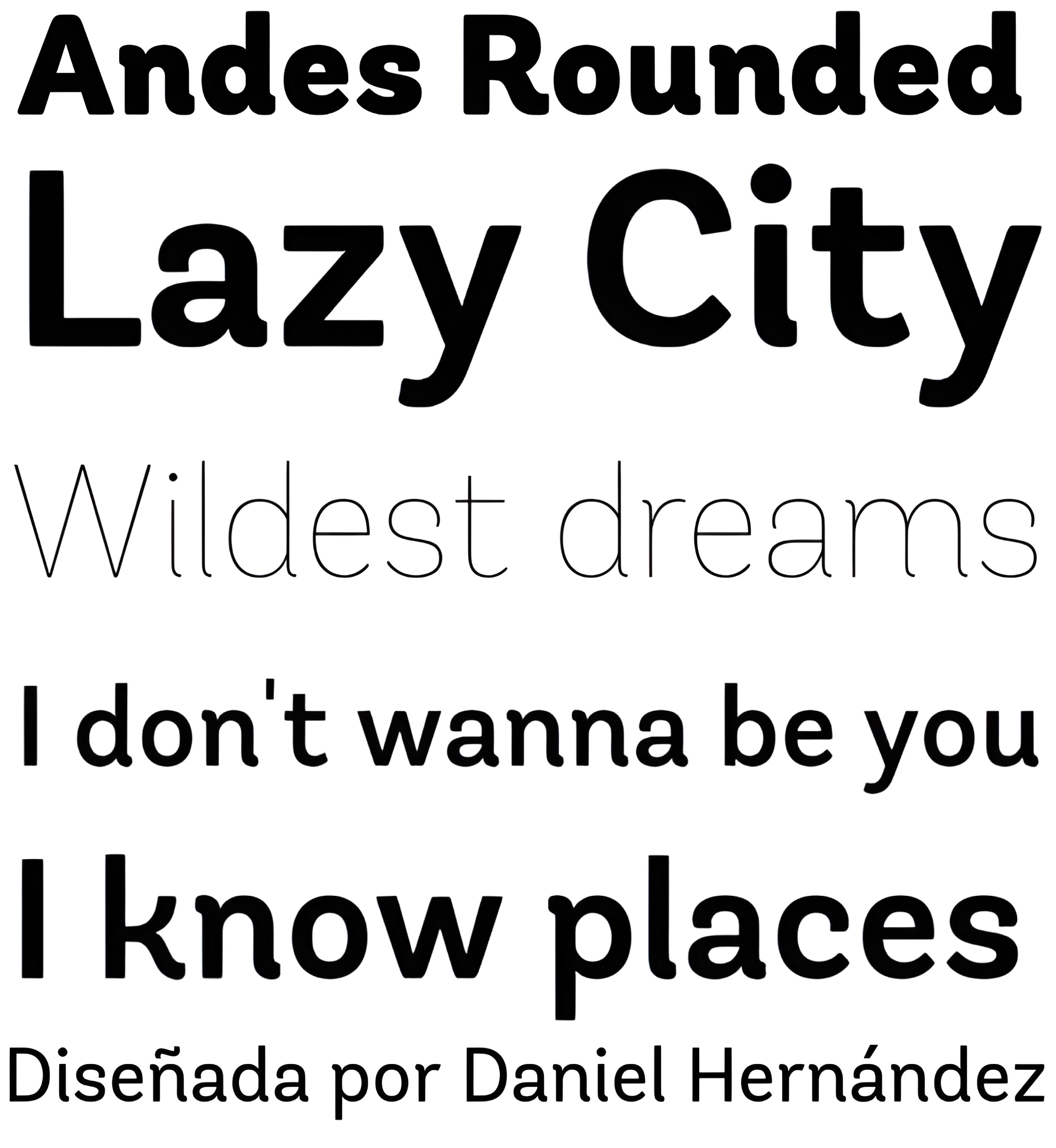
| Año | 2014 |
| Créditos | Daniel Hernández |
| Descripción | Andes Rounded, diseñado por Daniel Hernández, es un tipo de letra para pantalla de características neohumanistas. Sus diferentes terminales, entre otros elementos, le dan un aspecto de tipografía mixta. Andes es un tipo de letra con 10 Vertical pesas, 10 Cursiva & Versiones condensadasLos caracteres de este tipo de letra van de Ultra Light a Black, cada uno con la misma altura x. Este tipo de letra contiene glifos cursivos adicionales (a, y, z, g) que ayudan a enfatizar el texto o las palabras. Andes se basa en el diseño de Merced y ambos comparten varias características. Este tipo es muy adecuado para su uso en comercios, revistas, logotipos, libros, etc. |
| Familia(s) | Ultra Light, Extra Light, Book, Medium, Semi Bold, Extra Bold, Black |
| Estilos | 10 |
| Estudio | Latinotype |